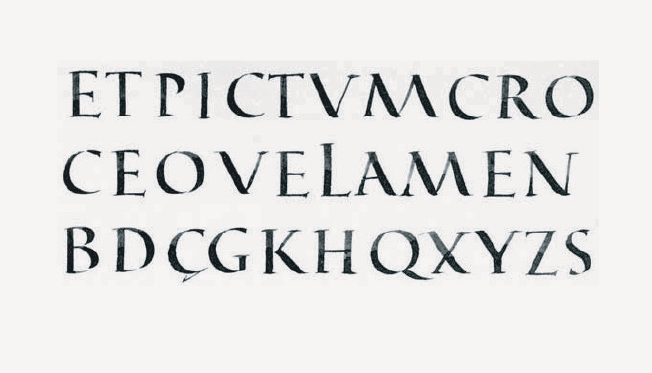
QUADRATA
Caligrafía. Es la versión manuscrita de las mayúsculas lapidarias romanas, las llamadas Trajanas. Es una forma de caligrafía solemne usada en la antigua Roma y durante el medievo.
La quadrata es uno de los tres estilos junto con la cursiva y la rústica que adoptó la caligrafía manuscrita romana.